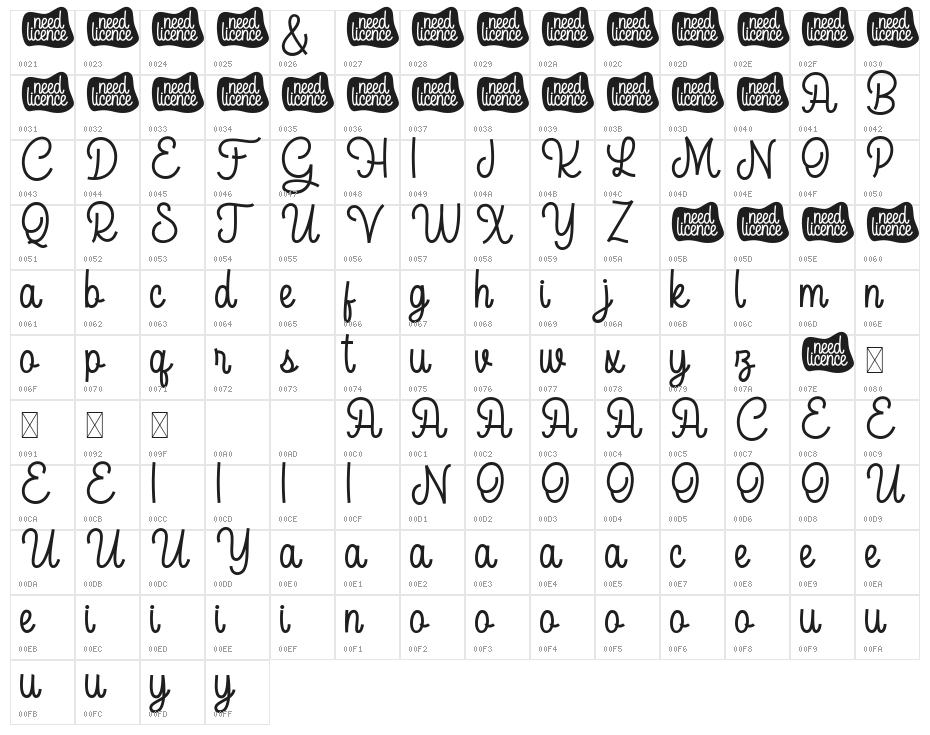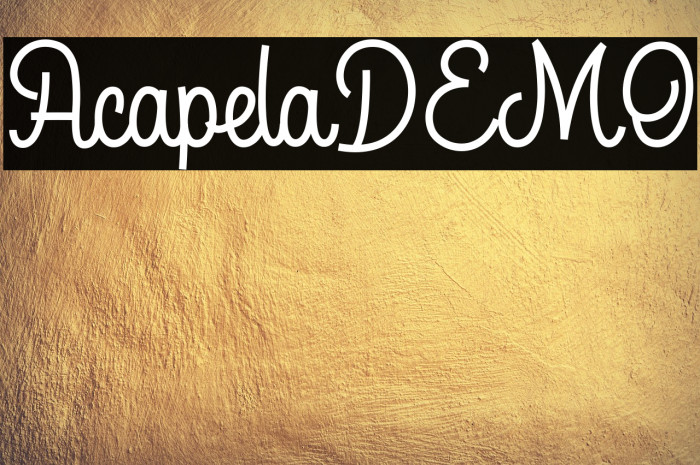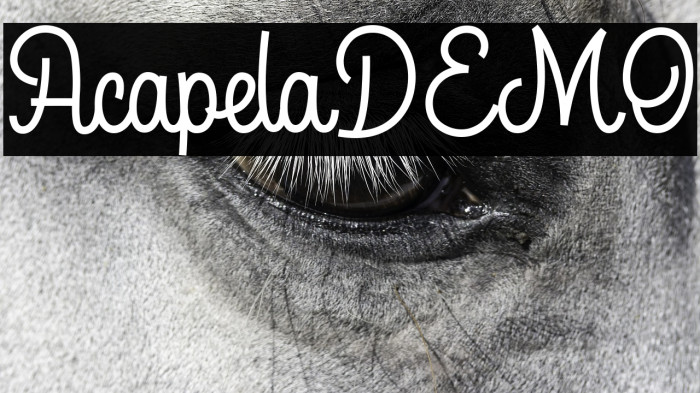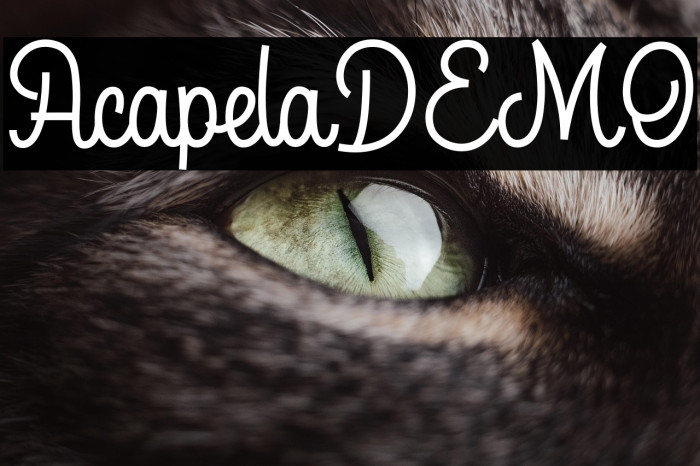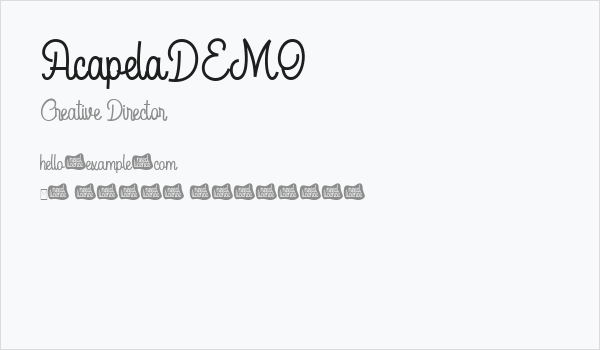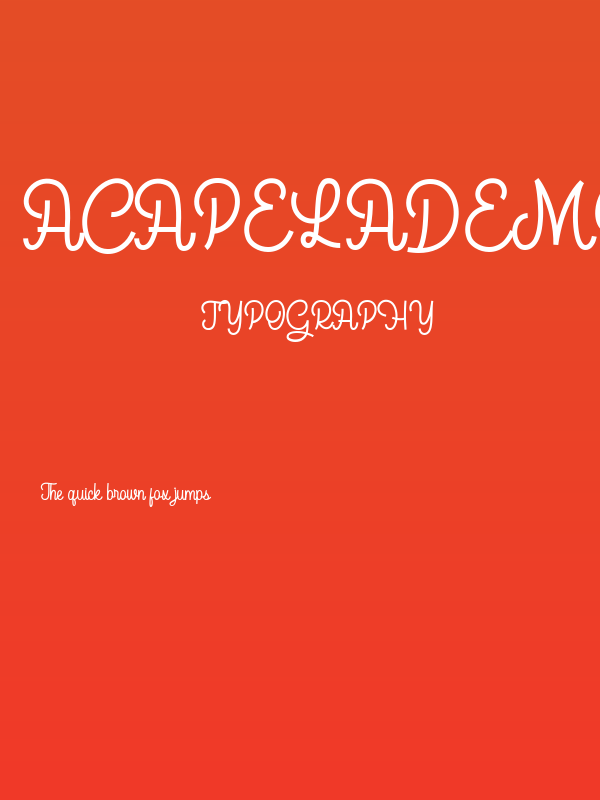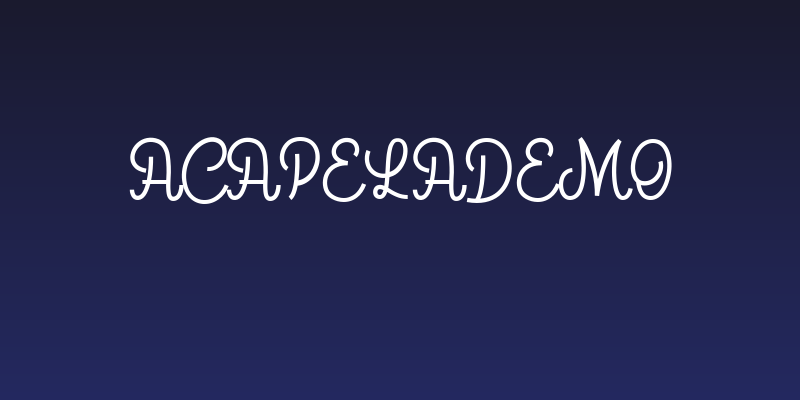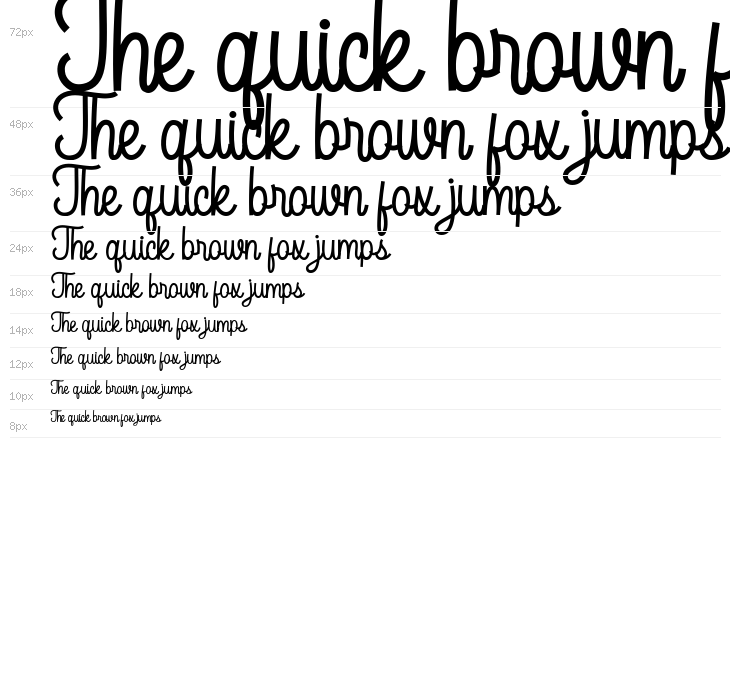
AcapelaDEMO Font
| حالة الاستخدام | Logos, Invitations, Creative projects |
| مشاريع مقترحة | Ideal for greeting cards, invitations, branding, and creative projects that require a personal touch. |